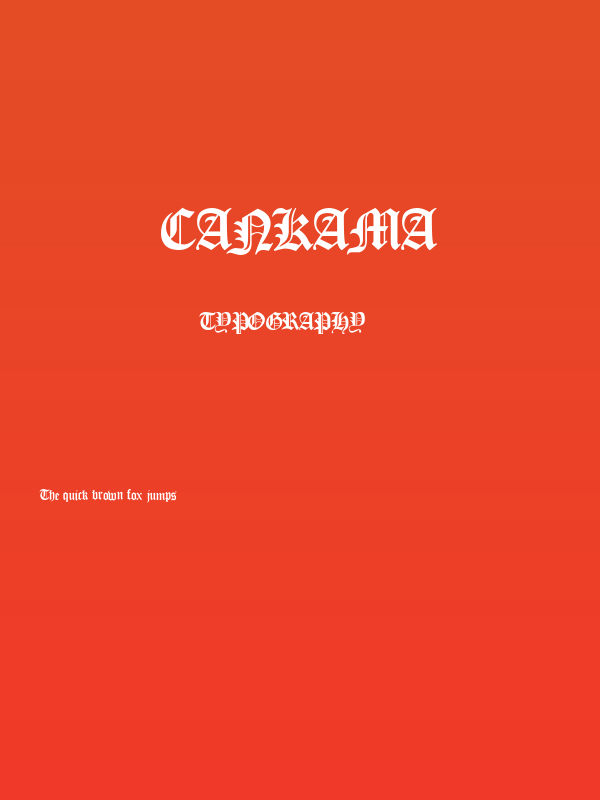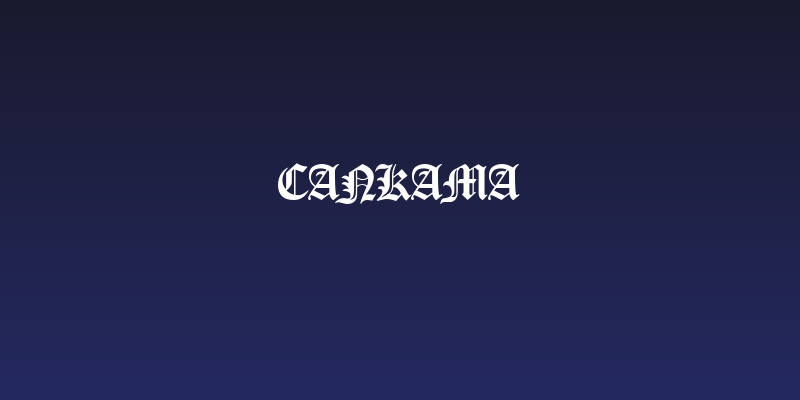
Cankama Font
✎ Gothic
| Kategorien | Gothic |
| Gesamtstil | Vintage |
| Anwendungsfall | Logos, Headlines, Decorative text |
| Vorgeschlagene Projekte | Ideal for historical documents, certificates, wedding invitations, and branding that requires a classic or medieval touch. |